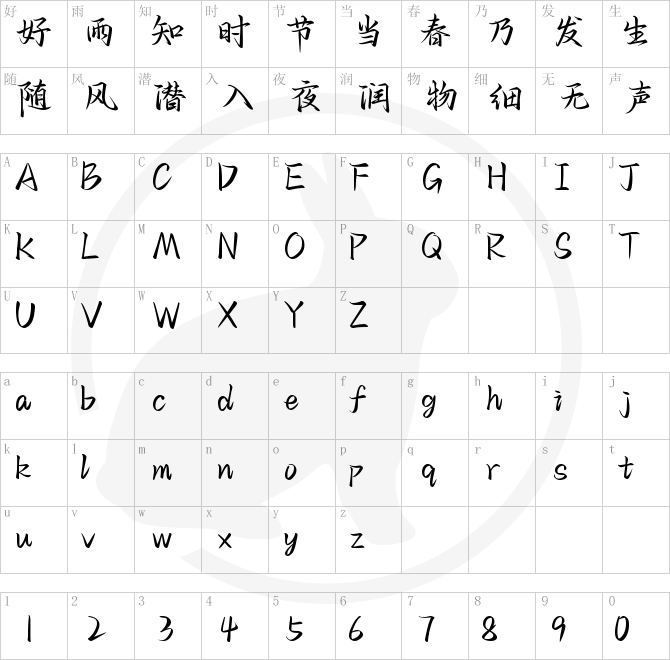
YEFONTYanShanTinXinKai 標準
YEFONTYanShanTinXinKai 標準,这款字体结构工整、笔画清晰,兼顾美观与易读性,适用于标题、正文、海报、包装、LOGO 等多种场景。字形优雅稳定,风格百搭耐看,适配日常排版与创意设计,让文字呈现更舒适、更具质感。YEFONTYanShanTinXinKai 標準一笔一画,皆是细节,以均衡的比例、流畅的线条打造舒适视觉体验,字形端正大气,风格简约现代。无论是商业设计、品牌宣传还是日常排版,都能轻松驾驭,让文字更有格调与力量。YEFONTYanShanTinXinKai 標準字体下载。